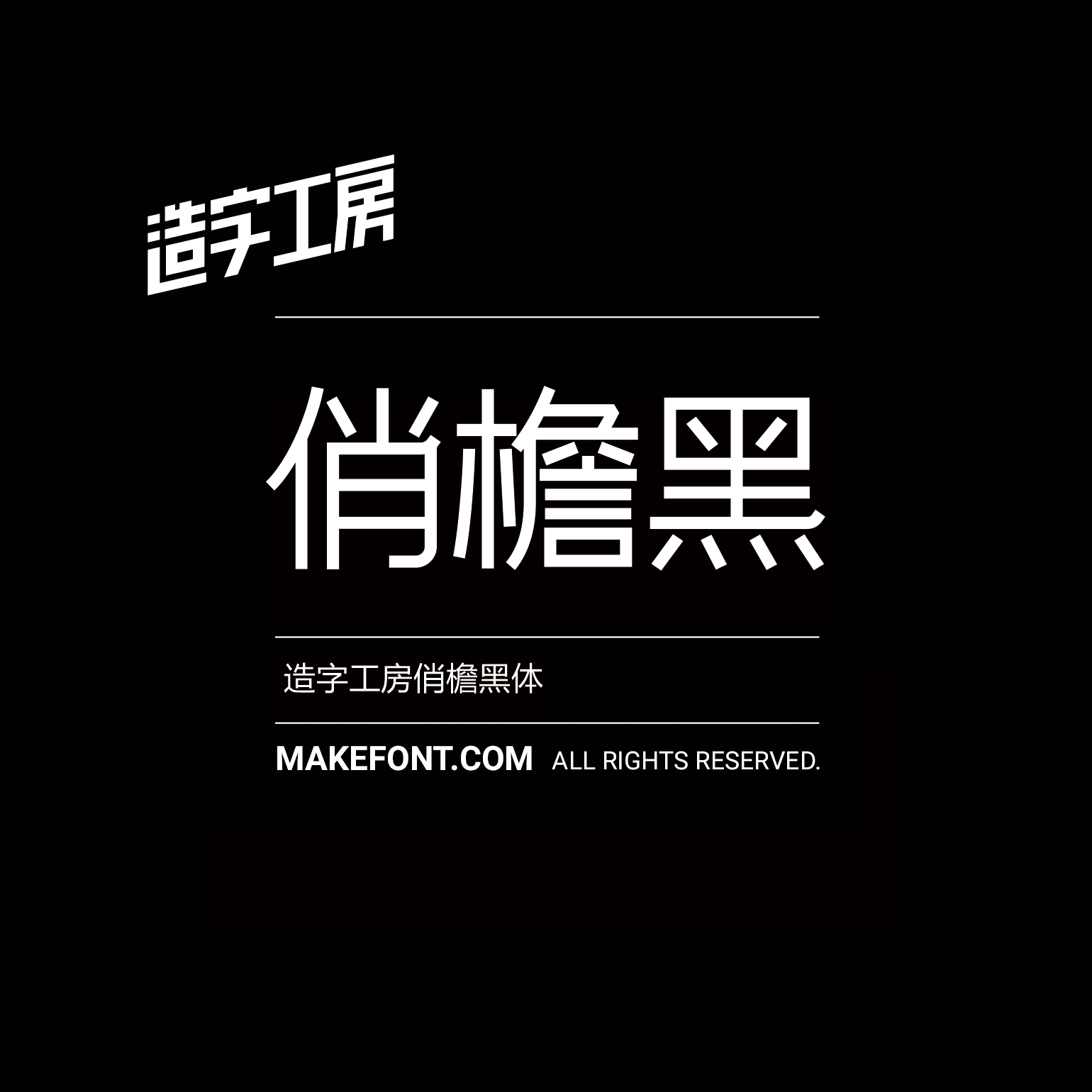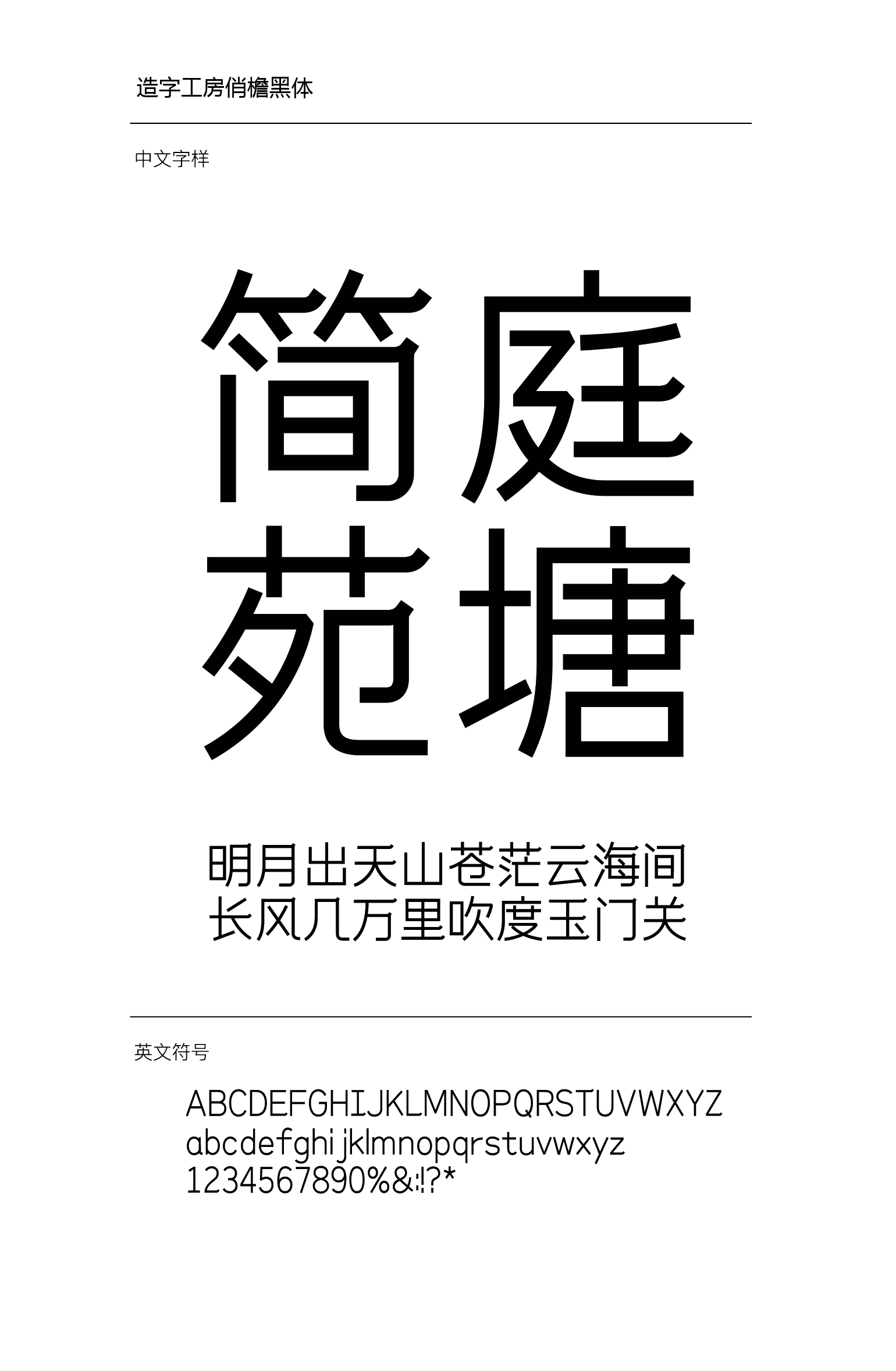
造字工房俏檐黑体设计说明
造字工房俏檐黑体是一款由传统黑体衍生而来的全新字体。笔画细致瘦长,字形方正端庄,部分收笔处向上扬起的俏角,如中式建筑中翘起的屋檐,字体纤细轻盈、灵巧活泼。本字体为简体字库,采用OpenType/CID格式,Adobe-GB1-5编码。基于中华人民共和国GB2312-80字符集标准,另按需添加101个汉字。共收容字数6864CJK汉字,ASCII常用字符100个。